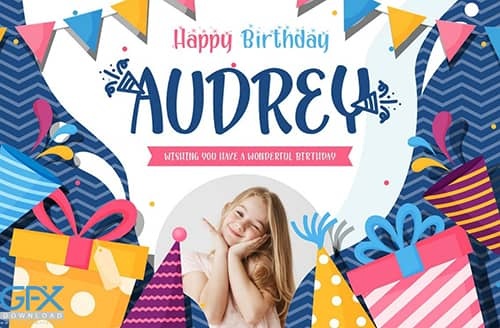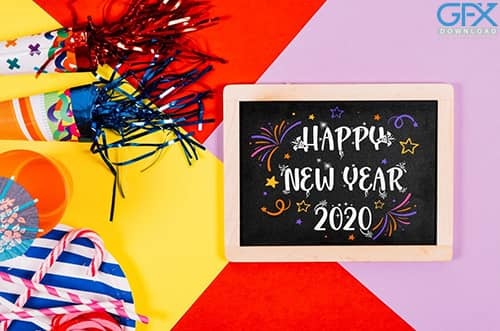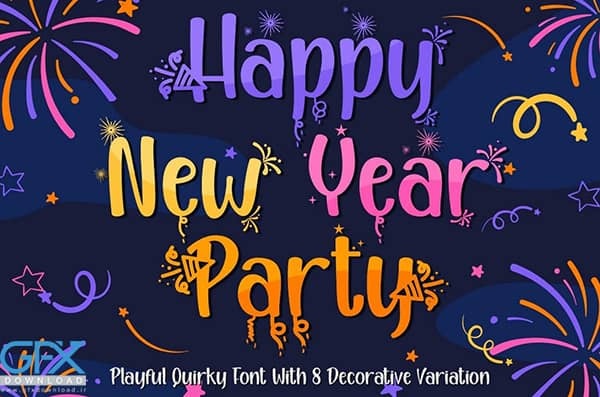
این فونت مناسب برای پارتی و مهمانی، سال نو، تبریک سال نو جدید و ... می باشد. فونت بسیار با انرژی و جذاب است که هر مخاطبی را جذب می کند. این فونت انگلیسی تبریک سال نو دارای 8 نسخه تزئینی است: معمولی ، آتش بازی ، پاشیدن ، روبان ، ستاره ، شیپور. این تزیینات مربوط به تزیینات سال نو می باشد ، و این فونت را کاملاً مناسب هر فعالیت / پروژه با مضمون سال جدید یا تعطیلات می کند. این فونت سال نو مبارک مناسب برای کاردستی ، هدیه ، رویداد کارت ، سالگرد ، تولد ، کارت تبریک ، لوگو تایپ ، برند تجاری ، پوستر ، بسته بندی ، لوازم التحریر ، وب سایت و سایر پروژه ها می باشد. همچنین فونت از چند زبانی پشتیبانی می کند.